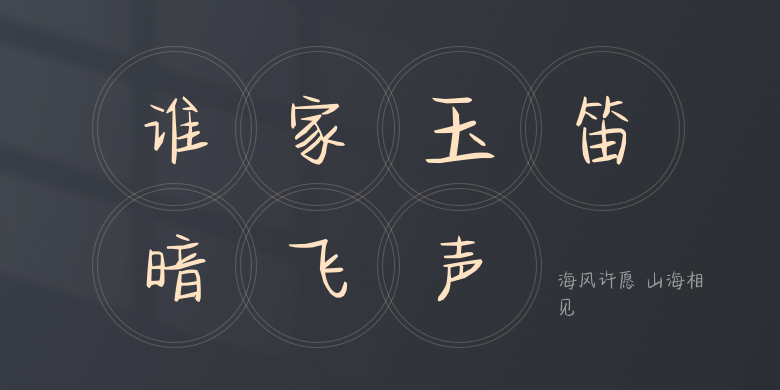
海风许愿 山海相见
海风许愿 山海相见,这款字体结构工整、笔画清晰,兼顾美观与易读性,适用于标题、正文、海报、包装、LOGO 等多种场景。字形优雅稳定,风格百搭耐看,适配日常排版与创意设计,让文字呈现更舒适、更具质感。海风许愿 山海相见一笔一画,皆是细节,以均衡的比例、流畅的线条打造舒适视觉体验,字形端正大气,风格简约现代。无论是商业设计、品牌宣传还是日常排版,都能轻松驾驭,让文字更有格调与力量。海风许愿 山海相见字体下载。